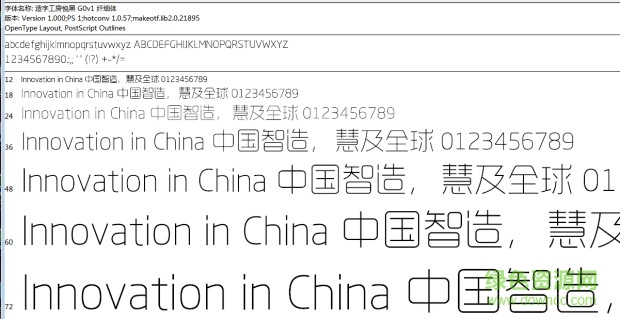
造字工房悅黑纖細(xì)體是造字工房中一款非常重要的字體哦,這款字體字形纖細(xì),但是顏色適中,也是使用的非常廣泛的字體哦,有需要的就來(lái)綠色資源網(wǎng)下載吧!
造字工房悅黑纖細(xì)體是一款極具個(gè)性的字體,該字體包具有多款不一樣的個(gè)性字體,讓用戶能夠任意選擇自己需要的字體,有喜歡的朋友可以來(lái)綠色資源網(wǎng)下載使用!